Deutsche Schrift
Vom Nordischen über Althochdeutsch, Mittelhochdeutsch und Frühneuhochdeutsch bis zum Neuhochdeutschen — die deutsche Sprache durchlief zwei große Lautverschiebungen und ebenso viele Schriftwandel. Eine Reise durch fast anderthalb Jahrtausende.
Sprachstufen im Überblick:
Eine Sprache wandert durch die Zeit
Die Stufen des Deutschen
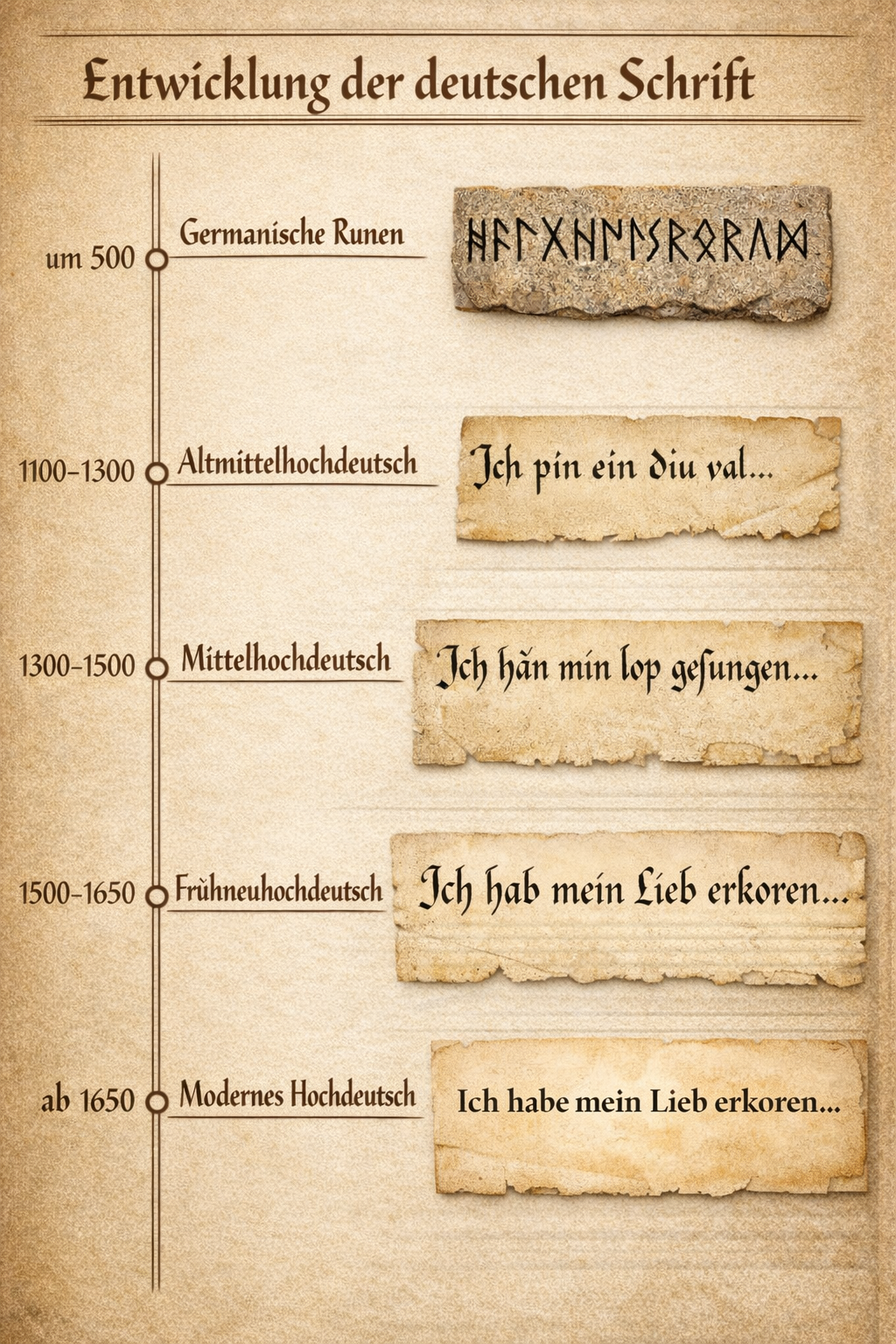
Vom Nordischen bis heute
Diese Übersicht führt durch die großen Etappen der deutschen Schriftgeschichte — vom frühen Nordischen über die karolingische Schreibstube und das höfische Mittelhochdeutsch bis zur Vereinheitlichung des Neuhochdeutschen. Jeder Balken in der Grafik führt direkt zur passenden Epoche.